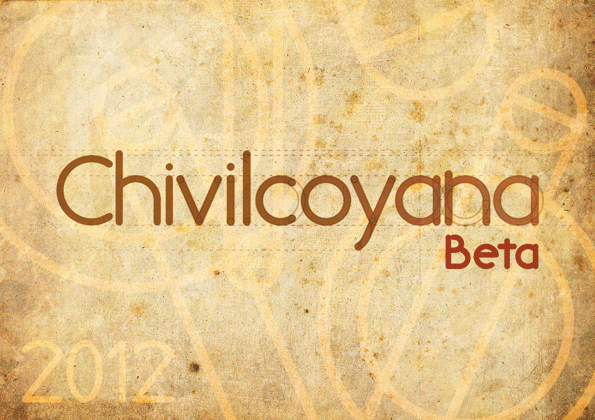
Preview and download Chivilcoyana Font. Created by Juan Ignacio Felice in Basic Sans serif styles with Free for personal use license.
Font name: | Chivilcoyana |
Author: | Juan Ignacio Felice |
Note by Juan Ignacio Felice | |
Chivilcoyana Regular es una versión Beta. La tipografía tiene un ancho fijo en sus trazos. Contiene mayúsculas, minúsculas, signos de puntuación, números y acentos. Faltan ligaduras y ajustes de kerning y tracking. Se permite el uso de esta tipografía SÓLO PARA USO PERSONAL. Gratis para uso personal. Donaciones serán bienvenidas. Para su uso comercial, contácteme a jifelice@gmail.com |